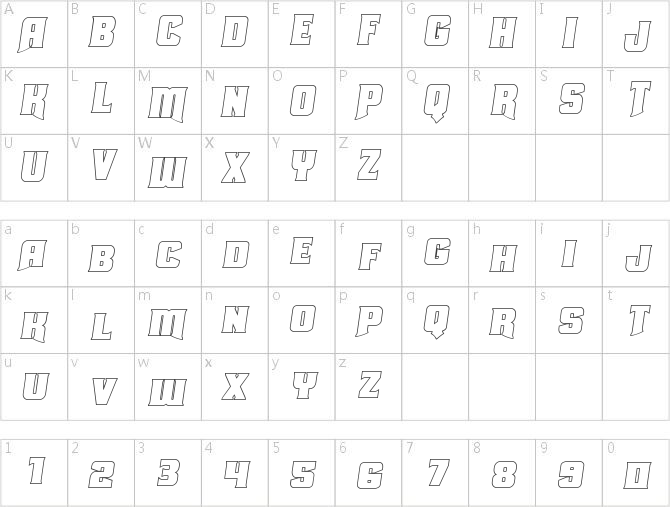
Union Gray Outline Semi-Italic 詳情頁
Union Gray Outline Semi-Italic字體字庫是一款讓人賞心悅目、百看不厭的英文字體,適合各類廣告和產(chǎn)品包裝設(shè)計應(yīng)用,字體大小0.07MB,格式為ttf字體,上傳用戶是13226568769,作者/版權(quán)方為未知